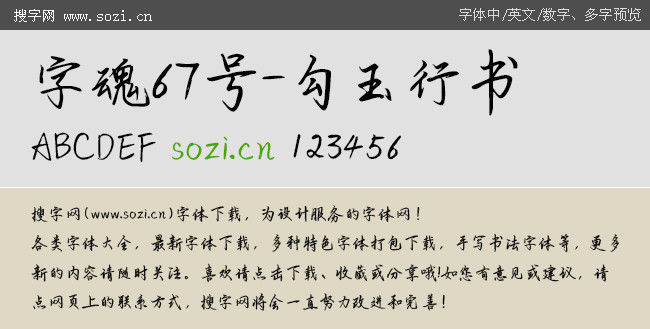
字魂67號(hào)-勾玉行書
搜字網(wǎng)提供一款字魂67號(hào)-勾玉行書中文字體下載,該字體是一款硬筆手寫字體,該字體包含9169個(gè)中文、字母、 符號(hào)和數(shù)字,具有古典、有力、優(yōu)雅、簡(jiǎn)約 的風(fēng)格,可以滿足您設(shè)計(jì)上的各種需求,該字體主要用于社交、屏幕、雜志、圖書、H5、活動(dòng) 等場(chǎng)景。